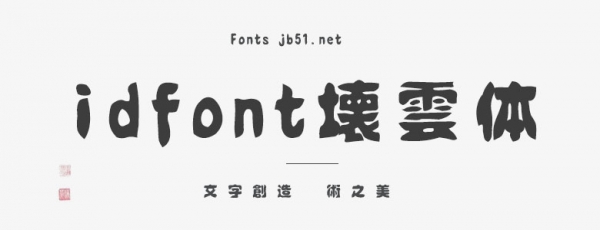
idfont壊雲体 繁体
带有略带复古特征的笔触字体。TrueTypeFont 和 OpenTypeFont 是公开的。
包括半角字母数字字符、全角字母数字字符、半角假名、全角假名、符号、全角假名、希腊字符、西里尔字符、格线、包围、单位、缩写和汉字。商业用途也是可能的。
根据字数软件统计这款字体包含简体中文字体4402个,其中常用字2470个,但是猫啃君发现其中不少字空白符号来占位的,所以实际上这款字体的字数并不多,连繁体也不算多。并且这款字体不允许嵌入软件分发,也不允许增补修改,十分可惜。大陆的小伙伴们用这款字体的话,就比较尴尬了。